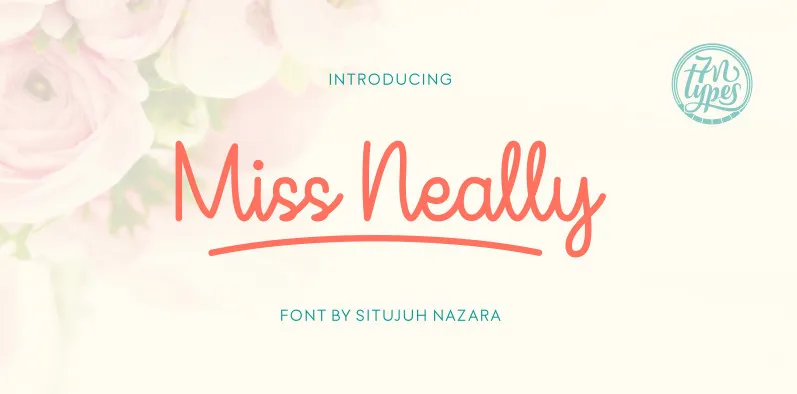
Miss Neally Script Font – Download Grátis
Através de nosso site, você encontrará Miss Neally, uma elegante e sofisticada fonte de script criada pela Situjuh Nazara. Esta fonte é um destaque na categoria de fonts de escrita à mão digital, junto com a famosa Stea e outras impressionantes criações typográficas. Hamilton é o designer responsável por Miss Neally. As características mais valorizadas desse charme são seu estilo suave e elegante. Uma das coisas mais interessantes que fazem desta fonte algo único é a inclusão de swashes para inicial e final em cada caractere, um recurso inovador que permite uma variação sofisticada ao usar a fonte. Esses bonus caracteres PUA estão codificados e são acessíveis em qualquer lugar. Além disso, as aplicações que suportam os recursos OpenType terão a opção de gerar automaticamente linhas traçadas abaixo do texto. A fonte também inclui sete diferentes variações para ampliar ainda mais seu uso em diversos tipos de projetos gráficos. Miss Neally não apenas é uma maneira incrivelmente criativa e bonita de escrever, mas também um recurso versátil que oferece flexibilidade ao designer. Não perca a oportunidade de experimentar esta fonte única – ela certamente fará sua marca em seus projetos digitais!